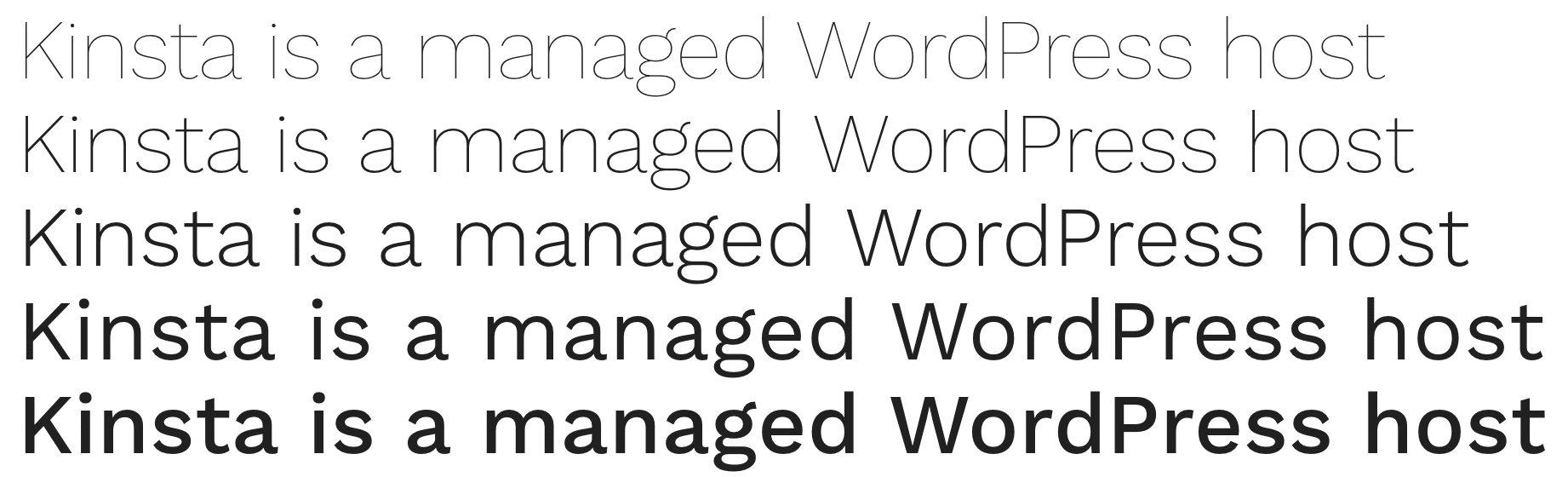
I skrivande stund finns det 884 olika Google Font-familjer tillgängliga gratis. Det är massor av valmöjligheter! Därför kanske du letar efter någon som hjälper dig att hitta den där nålen i höstacken med en lista över de bästa typsnitten från Google Fonts.
Att välja ett typsnitt är mer än bara ett estetiskt val – det kan ha en verklig effekt på webbplatsens avvisningsfrekvens och konverteringsfrekvenser, speciellt om du väljer ett typsnitt som är svårt för dina besökare att läsa.
Det lönar sig att ta sig lite tid att välja den bästa Google Fonts-familjen för din webbplats, istället för att bara välja det första typsnittet du ser!
De 10 bästa Google Fonts år 2019 – enligt allmänheten
Så hur kommer man fram med en lista över de bästa typsnitten från Google Fonts när så mycket av detta är subjektivt? Vi vill inte att hela listan ska vara subjektiv, så vi kommer att gå till insamlade data för att bygga en lista över de bästa typsnitten från Google Fonts.
Vi kommer i princip använda Google Fonts-analytics för att se vad många användare väljer och lita på att de valt det som fungerar. Med över 23 biljoner totalt antal typsnittsvisningar har Google lite data att utgå från. 😉
Sedan går vi lite utöver att bara titta på aktuell popularitet och väljer några av de nyare typsnitt som snabbt växer i popularitet. Redo? Låt oss dyka in…
1. Roboto
- Sans-serif
- Stilar: 12
Roboto Google font
Roboto är ett sans-serif-typsnitt från Christian Robertson som utvecklades av Google som systemtypsnitt för Android. Det är nu enormt populärt, kommer i 12 olika stilar, och gör flera framträdanden i Google Fonts analytics. Till exempel är Roboto det mest populära typsnittet. Men Roboto Condensed är också det sjätte mest populära typsnittet, och Roboto Slab dyker också upp som nummer 13!
2. Open Sans
- Sans-serif
- Stilar: 10
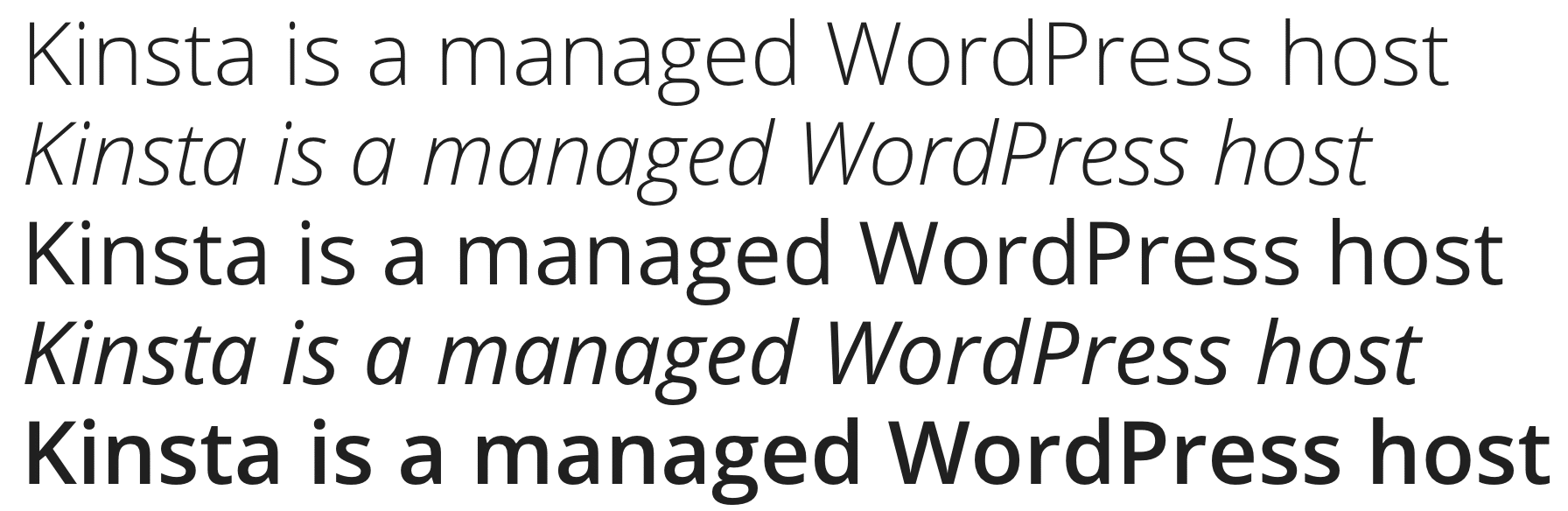
Open Sans Google font
Open Sans är ett sans-serif-typsnitt utvecklat av Steve Matteson. Google använder Open Sans på några av sina webbplatser, liksom i sina tryckta annonser och webbannonser.
3. Lato
- Sans-serif
- Stilar: 10
Lato Google font
Lato är ett annat populärt sans-serif-typsnitt, denna gång från Łukasz Dziedzic.
4. Slabo 27px/13px
- Serif
- Stilar: 2
Slabo Google font
Slabo är ett serif-typsnitt som utvecklats av John Hudson från Tiro Typeworks. Vad som är unikt med detta typsnitt är att det är speciellt utformat för att användas i en viss storlek – antingen 27px eller 13px beroende på dina behov.
5. Oswald
- Sans-serif
- Stilar: 6
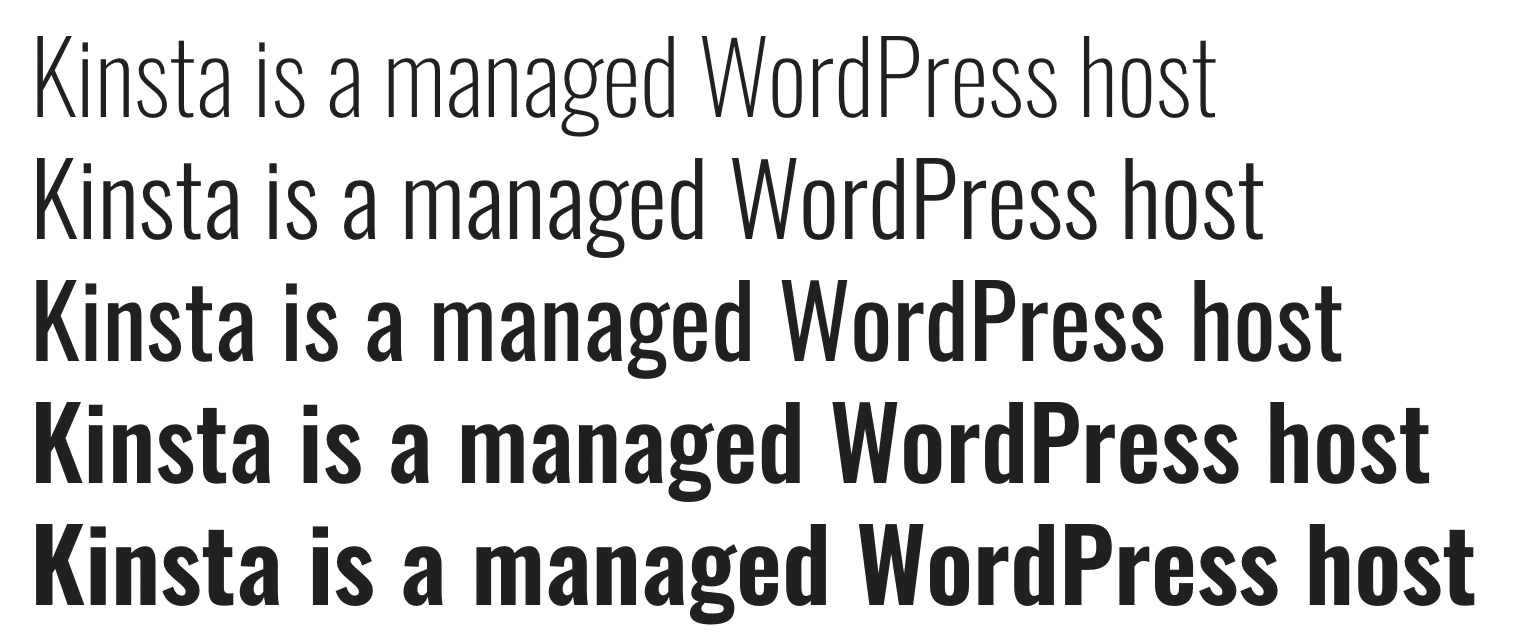
Oswald Google font
Oswald är ett sans-serif-typsnitt som ursprungligen utvecklades av Vernon Adams.
6. Source Sans Pro
- Sans-serif
- Stilar: 12
Source Sans Pro Google font
Source Sans Pro är ett sans-serif-typsnitt från Paul Hunt som skapades för Adobe och var Adobes första open-source-typsnitt.
7. Montserrat
- Sans-serif
- Stilar: 18
Montserrat Google font
Montserrat är ett sans-serif-typsnitt från Julieta Ulanovsky, som fick namnet från stadsdelen Montserrat i Buenos Aires där hon bor. Med 18 olika stilar har du ganska många valmöjligheter.
8. Raleway
- Sans-serif
- Stilar: 18
Raleway Google font
Med 18 olika stilar är Raleway en annan stor familj av sans-serif-typsnitt, ursprungligen skapad av Matt McInerney. Om du gillar Raleway och letar efter något unikt, erbjuder Raleway Dots liknande format men med ett prickat utseende som kan fungera för stora rubriker.
9. PT Sans
- Sans-serif
- Stilar: 4
PT Sans Google font
PT Sans utvecklades som de offentliga typsnitten för Ryska federationen och innehåller därför både latinska och kyrilliska tecken. Det finns också flera andra typsnitt i PT-familjen, inklusive några serif-alternativ.
10. Lora
- Serif
- Stilar: 4
Lora Google font
Lora är ett populärt serif-typsnitt som är utformat för att fungera bra både på skärmen och i tryck.
Bonustypsnitt + Snabbväxande nykomlingar
Enligt statistiken är de tio typsnitten ovan de mest populära från Google Fonts. Men att bara visa de mest populära alternativen är att inte vara rättvis mot några snabbt växande och nya typsnitt som ännu inte har fått exponering nog att dyka upp på analytics.
Här är några av våra favoriter som inte dök upp i toppen av listan.
11. Noto Sans / Serif
- Sans-serif eller serif
- Stilar: 4 av varje
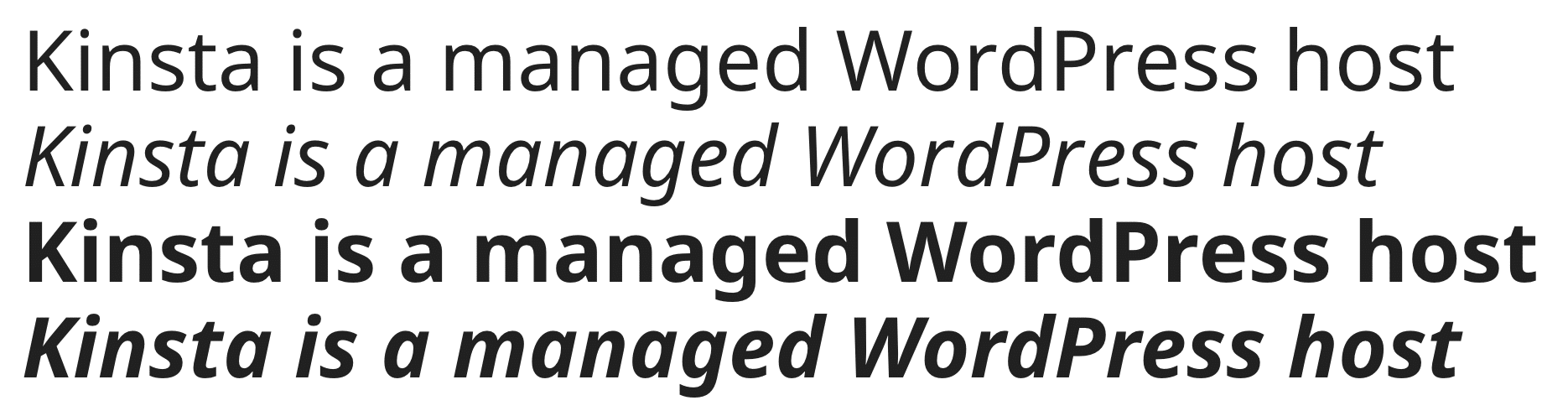
Noto Sans Google font